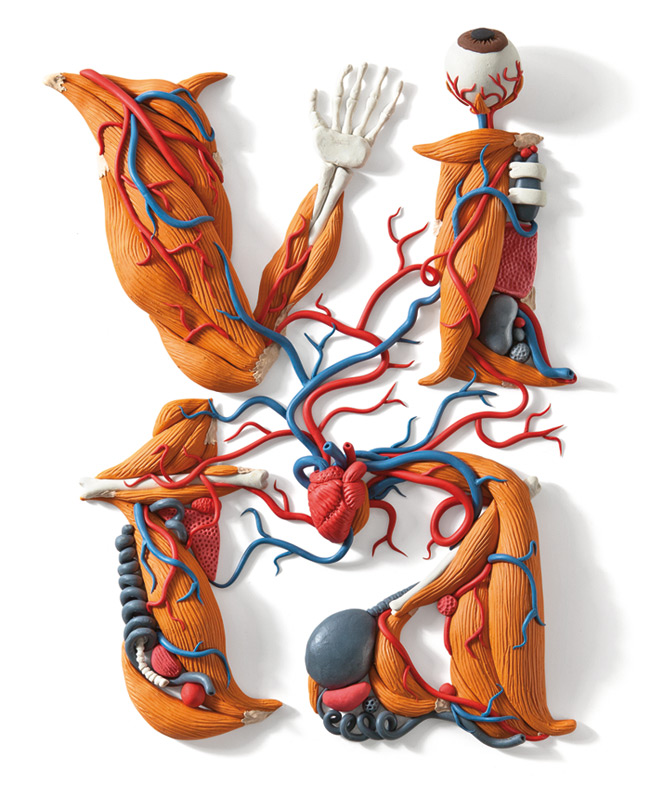
Andrea Manzati è un designer specializzato in illustrazione digitale, ma la cosa più impressionante dei suoi lavori, sono quelli tipografici interamente creati a mano.
Per questo particolare progetto commissionatogli dalla rivista italiana “Il“, ha utilizzato la plastilina, creando lettere decorate da parti del corpo umano e muscoli ottenendo l’effetto di far sembrare che stiano uscendo fuori dalle pagine del giornale.
Un’altro esempio dei suoi lavori in plastilina è quello per Fast Company Magazine a tema “food” che potete vedere qui per intero, mentre nella gallery c’è una piccola anticipazione.